什么是字体?
——什么使得手写、书法、印刷和 Logo 的字体样式不同?
使字体设计不同的一个最大的问题是需要字体样式中的每一个字形与其他字形的一起工作。这通常意味着字体样式中的每一部分的设计和间距最终要成为仔细折中的一个系列。这些折中意味着我们最好能够将字体样式设计看作是创造一个字母的美妙集合而不是一个美妙字母的集合。换句话说我们必须思考整体以及他们如何一起运转,并且其优先级要高于一个字母的精妙之处的问题。
这需要我们要使系统优先于每一部分,也导致了我们在系统的层面来分析我们的设计进程。特征超越字母成为我们想要关注的东西,尤其是在设计进程初期。
在字体设计中其他怪异的地方在于我们设计的形式在很大程度上已经显著建立。我们设计字体的任务并没有建立全新形式那么重,而是建立一个已有形式的新版本。这可能使新的字体设计者感到困惑。找到合适数量的改变来激励他们同时也不使读者感到疏远使一件棘手的事情。设计者通常会陷入具体字母的思考。如果你一开始意识到字体样式中最有意义的是其中重复最多的那些组成部分,那么能够很容易地避免这个错误。字体样式设计不是仅是关于设计特征应用在我们所认识的通用形式上,也是应用在最常出现的形式上。
特征不仅有助于创造字体的声音或者氛围,也能确定字体对什么有用或者没用,并且又是也有助于确定一个字体所适合的技术背景。认同这些是有帮助的。
按照这种方式思考字体设计可能是吓人的和过度抽象的。但是习惯这些想法是使得字体设计进程更加快速、高效和令人满意的关键。
让我们将识别字体设计的主要的系统特征作为开始。
结构
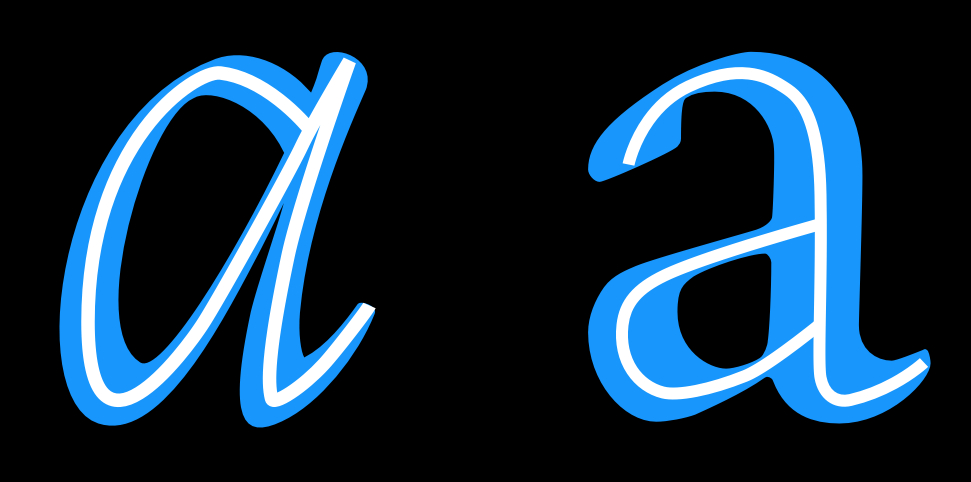
结构指的是形成特定字形的基础笔画的构造。你可以想象是字形的骨架。可以说采用什么构造是需要思考的最重要的问题之一,因为结构影响到如此多余下的选择,尤其是当你的设计需要让读者感到几分熟悉的时候。在上述例子中,字母中白色的线条指示出字母本身所暗含的粗略估计的结构。
但是末端的方式(终止节点)和衬线(如下)通常不是“结构”的含义的一部分。结构是一个字形的骨架,而剩下的——宽度、粗细、末端——都是血肉的一部分。
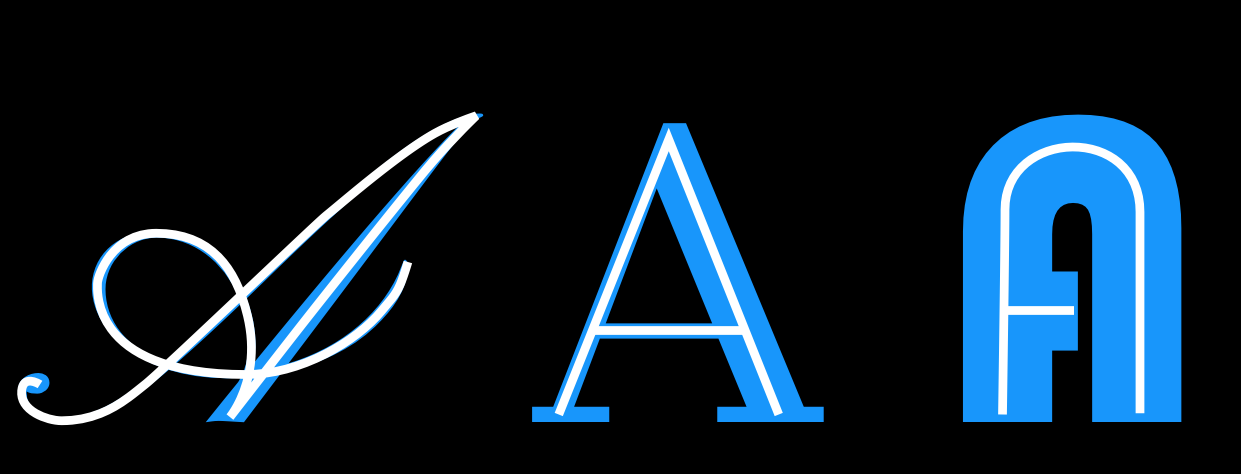
X 高度到大写高度的比例
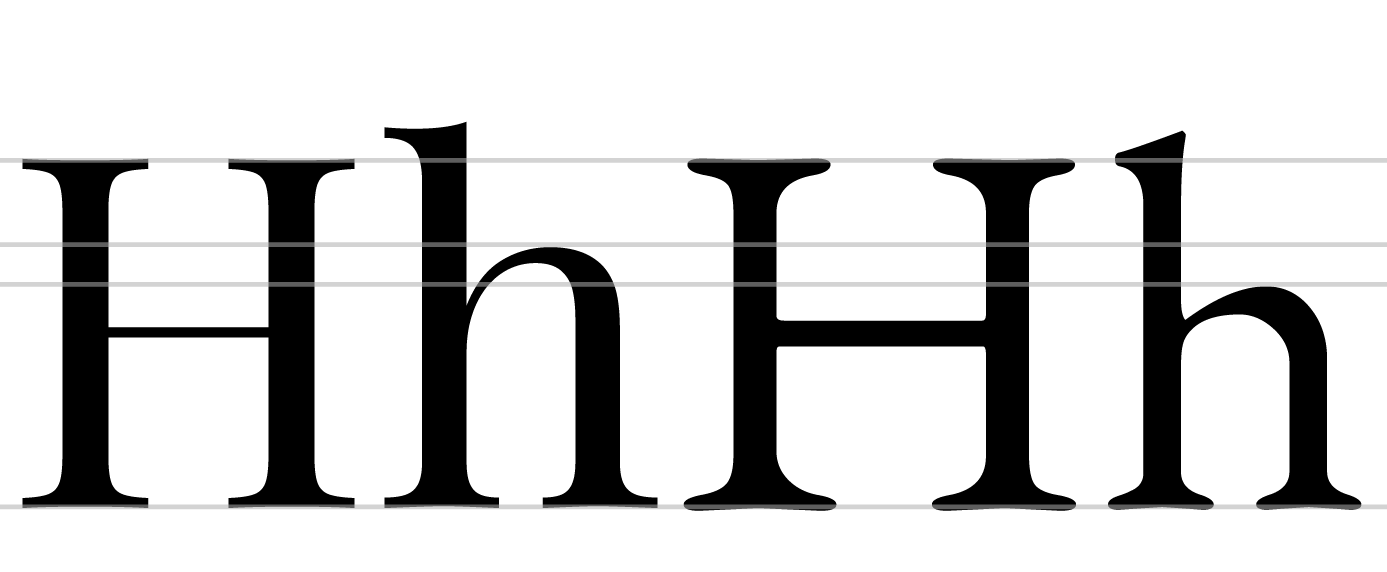
左边的字母来自 Playfair Display,相比于大写高度,x 高度较大。右边的字母来自 EB Garamond,X 高度较小。上面的例子中,字母 H 的高度被调整过,这样他们可以对齐。
顶高
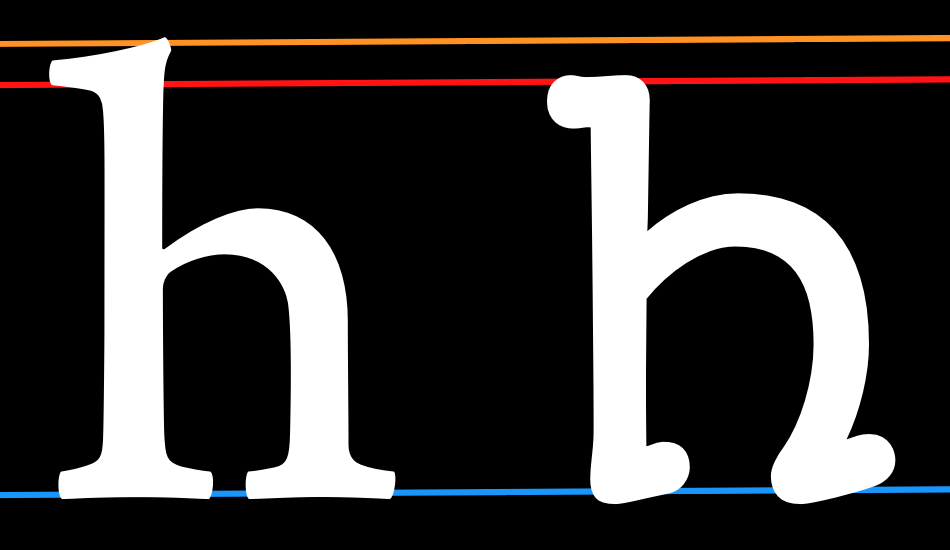
上面的例子中,为了演示在顶高上的相对差别,我们对齐了 X 高度。
顶高经常至少超过大写高度一点,尤其是在文字设计中。但是在某些情况下他们可能相等或者顶高比大写高度更低。更高的顶高能够让字体样式看起来更加优雅。他们通常 X 高度更小。
底深
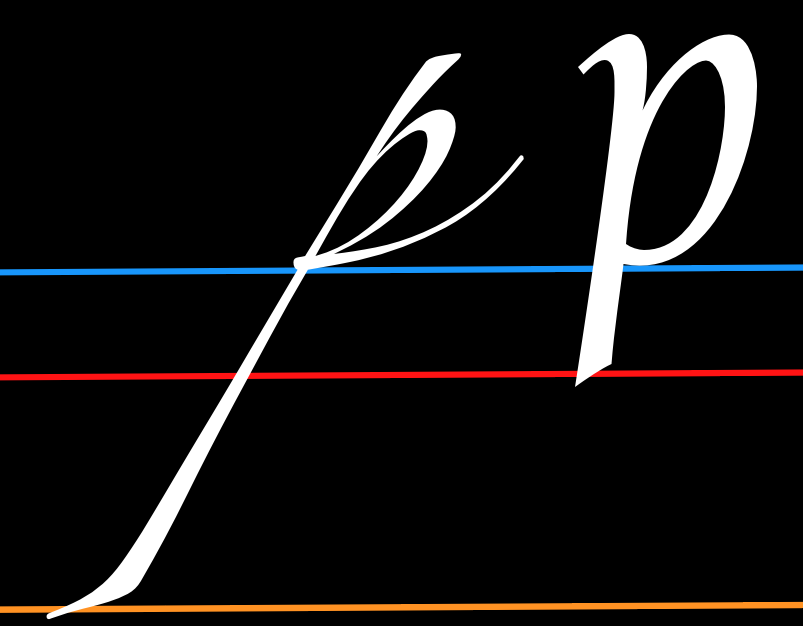
类似于顶部,更长的底部也能让人觉得更加优雅。
总之,更长的顶部和底部能够变得难以管理。如果字体样式使用了小的行高,典雅意味着字体可能跨越字体的行导致碰撞。
宽度
字体设计的宽度将不仅改变其感觉,也会改变其用途。右边的例子来自一个文本样式。左边的例子来自一个显示设计,目的是要醒目。字母比文本样式例子更加细,能够节约空间或者用于在小的空间内放下更多文本。
宽度不变与可变
上面的一行字母的宽度变化比下面一样要更大。
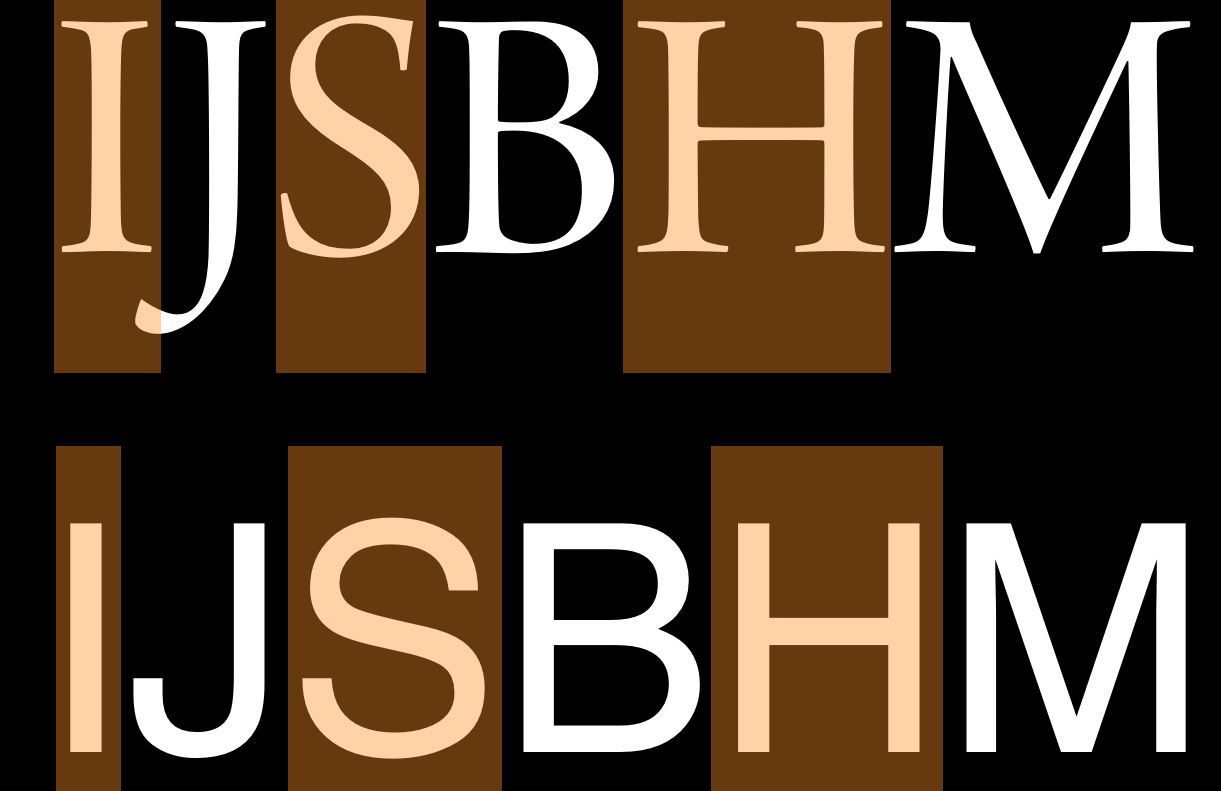
粗细
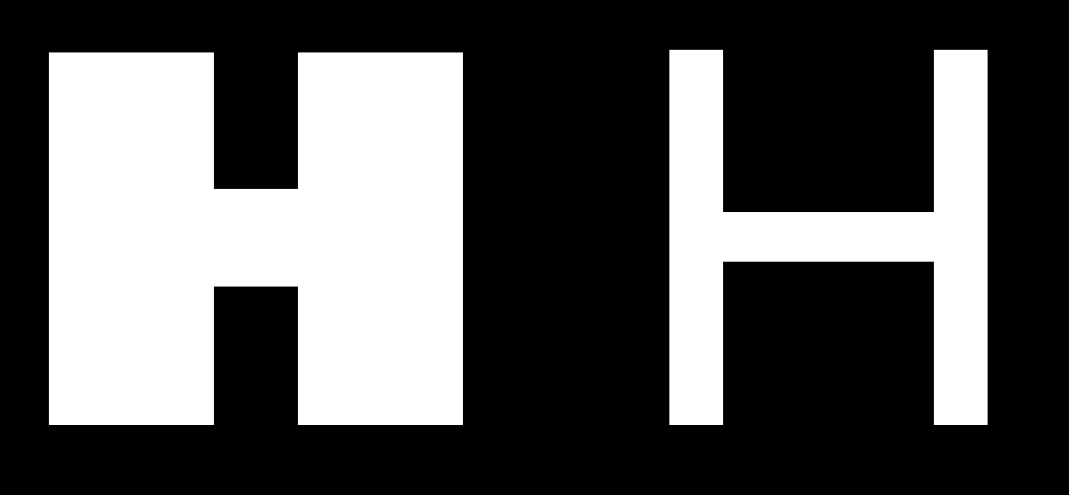
倾斜
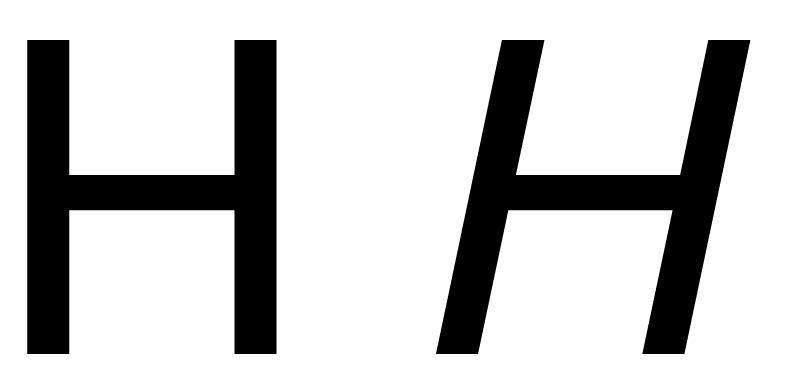
对比
对比指的是一个字形内能够找到多少笔画宽度的变化。注意在下面的两个“O”字形中,左边的从顶部到侧边的线条粗细比右边的变化更大。两个字形都有一些对比,但是左边那个字母的对比比右边的要大得多。
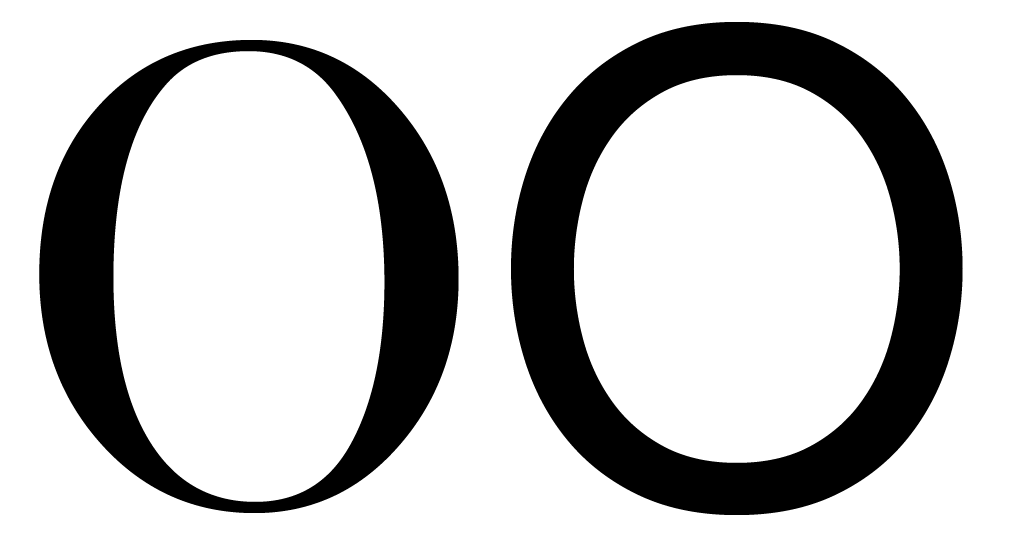
在其字母形式中有一致的粗细(笔画宽度)或者没有可见的对比的字体产生了与对比字体的完全区别。就像衬线与与无衬线之间的选择,对比时字体设计中的一个早期选择。有趣的是,厚衬线设计通常在字母中使用一致的笔画宽度。厚衬线设计不像听起来那样仅仅是关于衬线!需要记住的是感觉应用的规则(参见“相信你的眼睛”)——对比是关于粗细看起来怎样,而不是测量后应该是多少。
对比的角度
在下面的图中,我们看到小写字母“o”较细部分的形状是不同的。在左边的字形里,细的点完美地落在竖直轴上。在右边的字形中坐标轴是对角线。
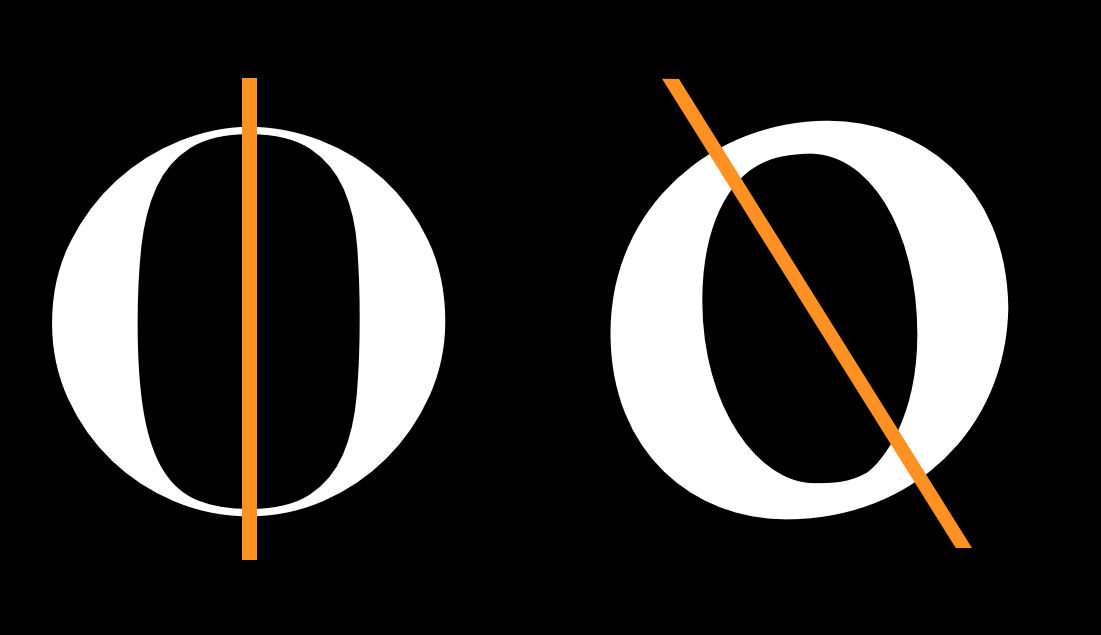
粗细分布
如果你很少使用对比,那么腻并不需要考虑它。但是大多数字体都包含一定程度的对比。在这些情况下,在你的字体中如何分布粗细将会有更加广泛的选择空间。
竖直
粗细的竖直分布很常见。上面的 9 和 8 是尤其强烈的例子。
水平
粗细的水平分布很少见,但是仍然能看到很多字体。
底重
顶重
不规则
茎
可能你容易假设你的茎会简单地呈笔直,这一点不是真正应该关心的。但是茎的粗细和形状是你应该做出深思熟虑的选择的。
连接
弧
需要注意的是弧(bowl,译者注:指的是在字符中创造出闭合空间的弧线笔画)指的是下面标示出来的笔画的部分,而不是内部的黑色部分。内部绘制的被称为“对立面”。在设计字体时,你可能经常发现需要修改你的作品,不是因为笔画的形状和宽度,而是由于对立面的形状和颜色。
末端
末端指的是末端的形式。它们与衬线是不同的。它们通常末端的角度的垂线,或者水平或竖直地修剪。它们也反映出笔尖的形状或者字母形式的其他创作工具。
速度
左边的“n”看起来比右边的字母写得要快很多。对速度更详细的讨论参见章节斜体。
规则性
下列特征并不会出现在所有的字体设计中,但是它们是可能成为你设计的一部分的可变因素。如果是这样的话,值得考虑它们作为可变因素的程度。
茂盛
需要注意的是上方字体的茂盛更多地体现在大写字母中,而第二个的茂盛更多地体现在小写字母中。
衬线
衬线是一个字体中最显著区别的方面之一。通常字体的一级分类就是衬线和非衬线字体。
这个选择影响了末端看起来怎么样。衬线可以是两端或者一端的。它们可以是垂直绘制的,或者有自己的方向(好像总是水平或者竖直的)。衬线可能有或者没有括号。任何衬线设计时上述的所有特征与特别字母的差异,尤其是“S”,“C”和“Z”,一致地应用在字体设计中(例如一个所有字母都包含水平衬线的字体的 s,c 和 z 字母经常有竖直的衬线。)。
一个都市传奇主张认为衬线字体笔比非衬线字体更易读——一个独特的迷思,直到另行通知。
衬线的形式与末端的形式相关。
支架
连接着主要笔画的衬线的拐角部分被称作“支架”。一个特别的设计可能采用它们来给衬线加入柔和感(Times New Roman 就是一个例子)或者可能选择不加支架。一些设计可能只在一端使用支架或者两端比例不同。
这是一个给字体渲染感觉的比较强烈的参数——优雅(Times New Roman 的平滑或大的支架)或者粗短干脆(Arvo 没有支架)。
厚板衬线
也成为机械或者埃及字体,厚板是厚的块状衬线。厚块衬线不使用支架。通常说来,又这样的衬线的字体设计在字形上会更少使用对比——Rockwell、Courier 或 American typewriter 体现了这一点。
我们可以可靠地假设厚板衬线使用来在一个其他方面没有对比的字体设计中加入装饰或者节奏。但这也不是绝对的规则。
衬线结束
就像字母结束那样,衬线本身的结束形状对字体的感觉有帮助——使其柔软或短粗。衬线结束可以是柔软圆角的(Courier)或者有棱角的(Rockwell)。
装饰
维度